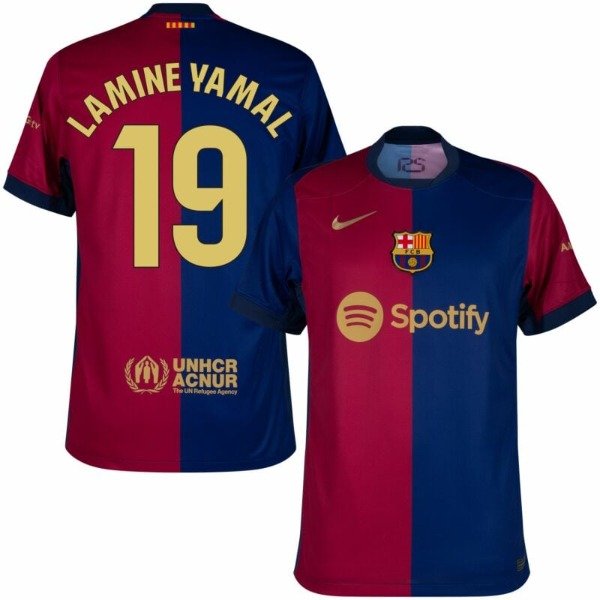
NUEVA! Tipografía Números Fuente Camisetas 2025 2026 BARCELONA
Tipografía Números Fuente 2025 NUEVA EQUIPACIÓN
-La tipografia ES TAL CUAL SE VE EN LA PRIMER IMAGEN - incluye logos
Realizá todo tipo de creaciones con la tipografía utilizada actualmente en el club